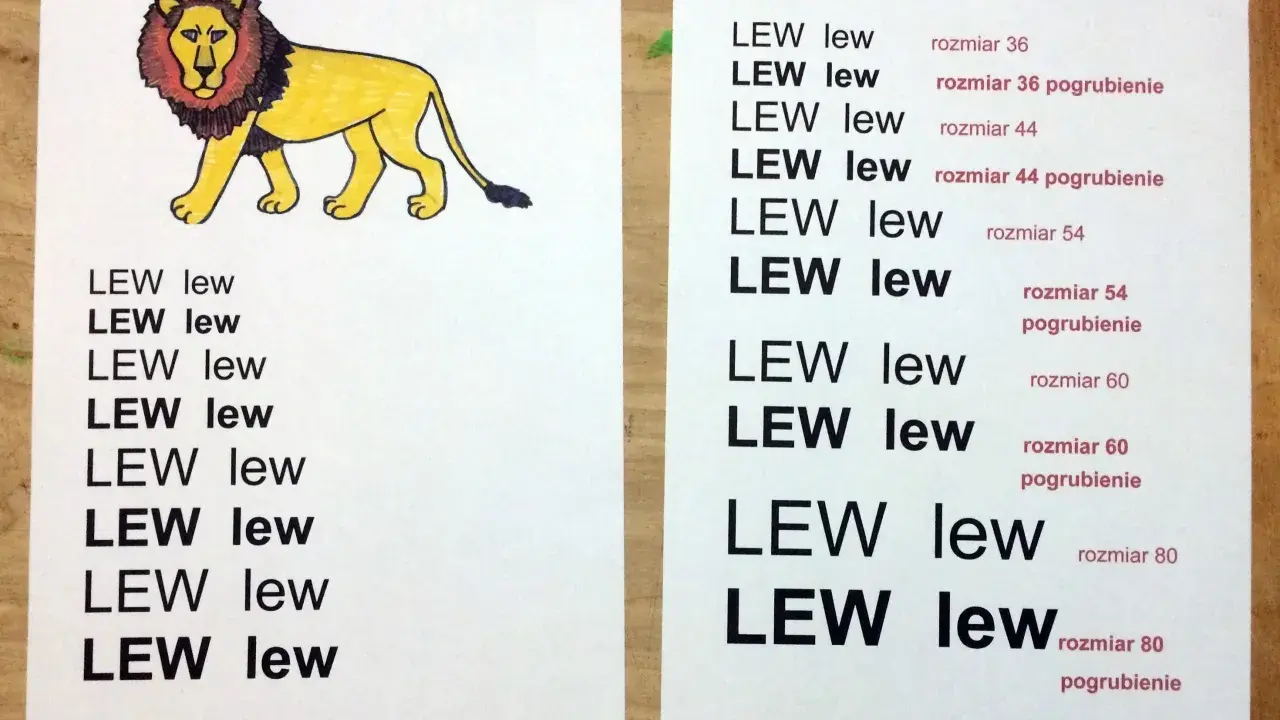
Dobra czcionka dla dzieci nie musi być ozdobna ani przesadnie „młodzieżowa”. W materiałach edukacyjnych liczą się przede wszystkim wyraźne litery, sensowny odstęp i prosty rytm tekstu, bo to one decydują, czy dziecko czyta swobodnie, czy szybko się męczy. Poniżej pokazuję, które kroje naprawdę warto rozważyć, jak dobrać je do wieku i zadania oraz jakie ustawienia składu robią większą różnicę niż sam wybór fontu.
W dobrym materiale dla dzieci liczą się prosty krój, odpowiednie odstępy i dopasowanie do wieku
- Do nauki czytania najlepiej sprawdzają się proste kroje bez zbędnych ozdobników.
- W praktyce bardzo dobrze wypadają ABeeZee, Andika, Verdana, Tahoma, Lexend i Nunito.
- Nie ma jednego uniwersalnego zwycięzcy, bo inny krój wybieram do kart pracy, a inny do planszy lub PDF-u.
- Przy pierwszym czytaniu ważniejsze od stylu liter są interlinia, kontrast i wielkość tekstu.
- W druku zaczynam zwykle od 12–14 pt, a przy materiałach dla początkujących podnoszę to do 14–16 pt.
- W materiałach cyfrowych duże znaczenie ma też wyrównanie do lewej i unikanie zbyt ciasnego składu.
Co naprawdę decyduje o tym, czy krój jest dobry dla dziecka
W typografii precyzyjniej mówi się o kroju pisma niż o samej czcionce, ale w praktyce chodzi o to samo: o zestaw liter, który ma być czytelny, wygodny i konsekwentny. Ja zawsze zaczynam od pytania, czy dany krój pomaga dziecku rozpoznać litery bez zbędnego wysiłku.
Najważniejsze cechy są dość przyziemne. Szukam wyraźnych wnętrz liter, prostych zakończeń, sensownego rozróżnienia znaków podobnych wizualnie, takich jak l, I i 1, oraz bezpiecznej grubości kreski, która nie znika po wydruku. W materiałach dla młodszych dzieci dobrze działają też formy otwarte i niezbyt ciasne, bo dają więcej oddechu przy czytaniu.
- Czytelność w małym rozmiarze - krój ma działać nie tylko w nagłówku, ale też w krótkiej notatce lub zadaniu.
- Wyraźne litery - szczególnie ważne przy podobnych znakach i polskich diakrytykach.
- Umiarkowana grubość - zbyt cienkie litery znikają na słabszym papierze lub przy niższym kontraście.
- Spójny charakter - font może być przyjazny, ale nie powinien rozpraszać ozdobnością.
W skrócie: do edukacji dziecięcej wygrywa najczęściej prostota, a nie efekt „wow”. Z takim kryterium łatwiej już ocenić konkretne kroje, które naprawdę warto przetestować w praktyce.
Kroje, które w praktyce sprawdzają się najlepiej
Google Fonts opisuje ABeeZee i Andikę jako kroje tworzone z myślą o nauce czytania i pisania, dlatego od nich zaczynam, gdy przygotowuję materiały dla młodszych odbiorców. Nie traktuję jednak żadnego fontu jak cudownego rozwiązania - dobry wybór zależy od tego, czy tworzę kartę pracy, planszę, czy materiał do czytania w domu.
| Krój | Gdzie działa najlepiej | Dlaczego go wybieram | Na co uważać |
| ABeeZee | Wczesna nauka czytania, krótkie karty edukacyjne | Jest prosty, otwarty i bardzo przyjazny w odbiorze | W bardzo małym stopniu może wyglądać zbyt miękko |
| Andika | Elementarz, alfabet, materiały dla początkujących | Ma czytelne, jasno zbudowane litery i powstał z myślą o alfabetyzacji | Jest rzeczowy, więc do bardziej dekoracyjnych projektów bywa zbyt neutralny |
| Lexend | Teksty cyfrowe, dłuższe bloki informacji | Dobrze redukuje zmęczenie wzroku i ma przyjazne proporcje | Warto przetestować w druku, bo w PDF-ach i na ekranie zachowuje się nieco inaczej |
| Verdana | Instrukcje, karty pracy, teksty pomocnicze | Ma szerokie światła i świetnie trzyma czytelność w mniejszych rozmiarach | Zajmuje sporo miejsca, więc dłuższy tekst szybko się rozrasta |
| Tahoma | Podpisy, formularze, krótsze polecenia | Jest zwięzła i wyraźna, dobrze działa w uporządkowanych układach | W długich akapitach może być mniej „oddychająca” niż Verdana |
| Nunito | Plansze, etykiety, nagłówki | Ma miękki, przyjazny rytm i dobrze wygląda w komunikatach dla dzieci | Do ciągłego czytania trzeba ją sprawdzić w docelowym rozmiarze |
| Arial | Bezpieczna baza do większości materiałów | Jest neutralny, prosty i powszechnie dostępny | Bywa zbyt bezcharakterny, jeśli zależy Ci na bardziej dziecięcym odczuciu |
| Century Gothic | Plakaty, krótkie hasła, dekoracyjne nagłówki | Wygląda lekko i nowocześnie | W dłuższym tekście łatwo myli podobne litery |
Jeśli mam wybrać tylko kilka krojów na start, biorę zwykle Andikę, ABeeZee i Verdana. Ten zestaw daje mi bezpieczną bazę zarówno do nauki czytania, jak i do prostych materiałów szkolnych, a potem mogę już dobrać styl do konkretnego wieku i zadania.
Jak dobrać krój do wieku, zadania i nośnika
Nie projektuję materiałów dla dzieci tak, jak projektowałbym ulotkę czy ofertę firmową. Inaczej dobieram font do przedszkolaka, inaczej do ucznia, który czyta samodzielnie, a jeszcze inaczej do planszy albo PDF-u otwieranego na telefonie.
Przedszkole i zerówka
Na tym etapie stawiam na kroje o prostych kształtach, dużych oczkach liter i wyraźnym rytmie. Dziecko ma dopiero oswajać się z literą, więc krój nie powinien udawać kaligrafii ani wyglądać jak ozdobny napis z plakatu.
- Do kart pracy - Verdana lub Tahoma, 12–14 pt, wyrównanie do lewej i dużo miejsca na odpowiedź.
- Do plansz i etykiet - Nunito lub Century Gothic, większy stopień pisma i ograniczona liczba słów.
- Do PDF-ów i materiałów cyfrowych - Lexend, Verdana lub Andika, z testem na telefonie przed publikacją.
Jeśli miałbym zostawić jedną zasadę na koniec, byłaby bardzo prosta: w materiałach dla dzieci wygrywa ten krój, który znika w tle i pozwala skupić się na treści. Ozdobność może pomóc w nagłówku, ale w samym tekście lepiej pracuje prostota, przewidywalność i czytelny rytm liter.